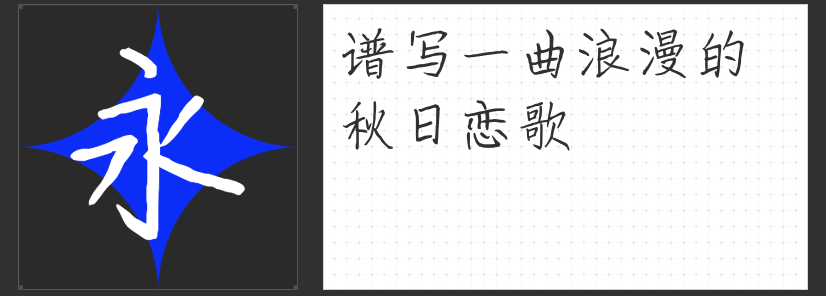
手写风情,设计新宠:四款创意手写字体推荐
在设计的广阔天地里,字体不仅是信息的载体,更是情感的传递者。今天,就让我们一同探索四款专为设计而生的手写字体,它们各自以独特的风格,为设计作品增添无限魅力。
当圆润遇见可爱,设计因此温馨。这款字体以其饱满的字形,勾勒出一个个仿佛会笑的字符,自然流畅的弧线与柔和转角,让人一眼难忘。无论是儿童书籍的封面,还是品牌宣传的海报,它都能完美融入,传递出纯真无邪的亲和力,让目标受众心生喜爱。
笔触间的随性,是青春的记忆。这款字体带着一丝稚气与可爱,仿佛初中生笔下的涂鸦,轻松自在,又不失个性。它适合那些想要传达轻松愉悦氛围的设计项目,如旅行日志、休闲品牌宣传等,让人仿佛回到了那个无忧无虑的年纪。
雅致与灵动,秋风中的浪漫诗篇。字体的点画自然流畅,结体舒展而不失雅致,给人以风吹落叶般的轻盈感。无论是邀请函、文艺杂志还是高端品牌宣传,它都能以其独特的韵味,营造出一种静谧而深远的视觉享受。
4.小豆岛默陌枝桠简
水墨意蕴,书写自由之魂。这款字体融合了传统书法的写意与现代设计的简约,通过细腻的运笔节奏,展现出枯枝藤蔓般的造型美。它适用于追求文化深度与自然美感的设计作品,如书法展览海报、茶文化宣传等,让人在字里行间感受到那份超脱与肆意。
这四款手写字体,各具特色,不仅丰富了设计的语言,更为作品赋予了独特的灵魂。选择适合的字体,让设计不仅仅是视觉的盛宴,更是情感的共鸣。